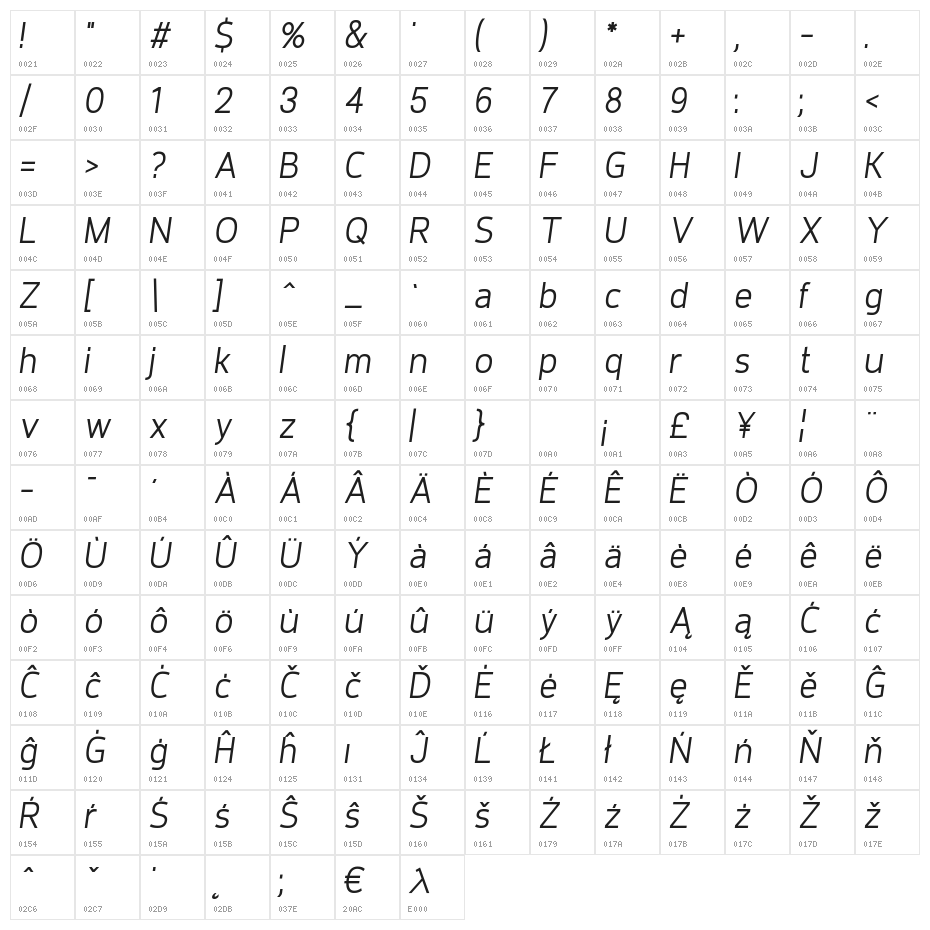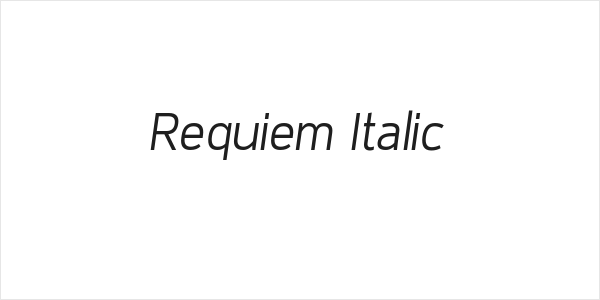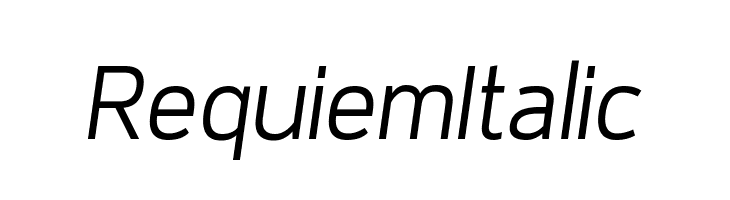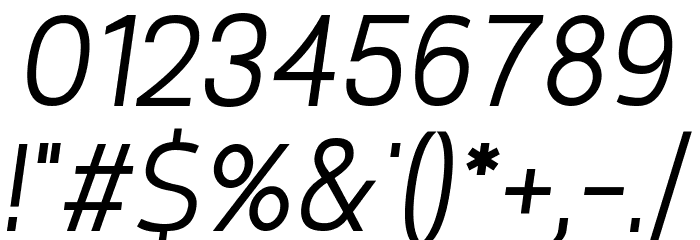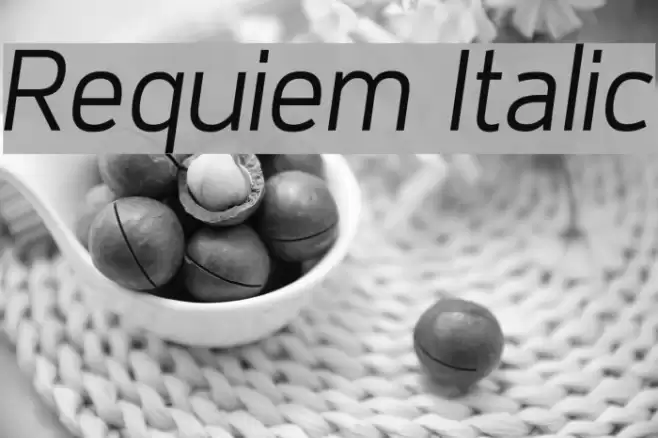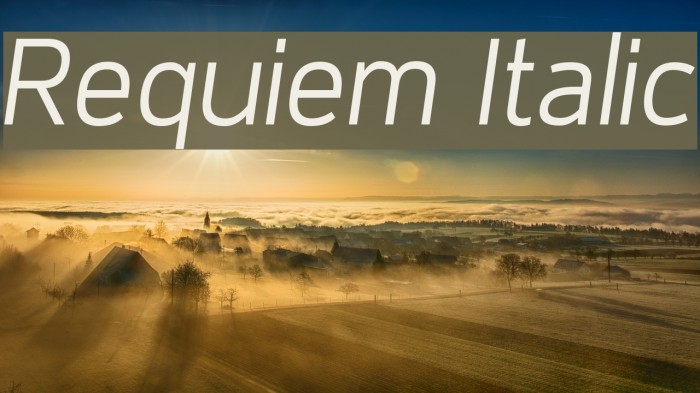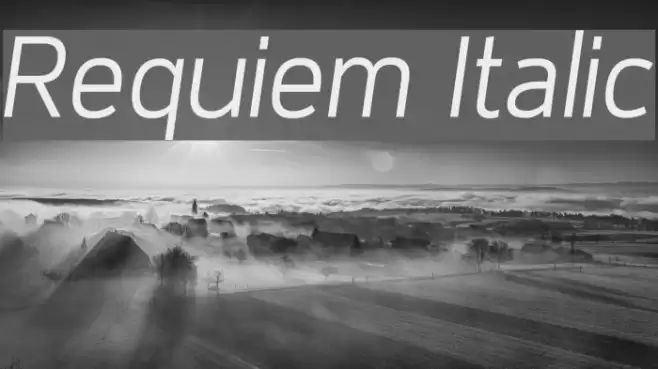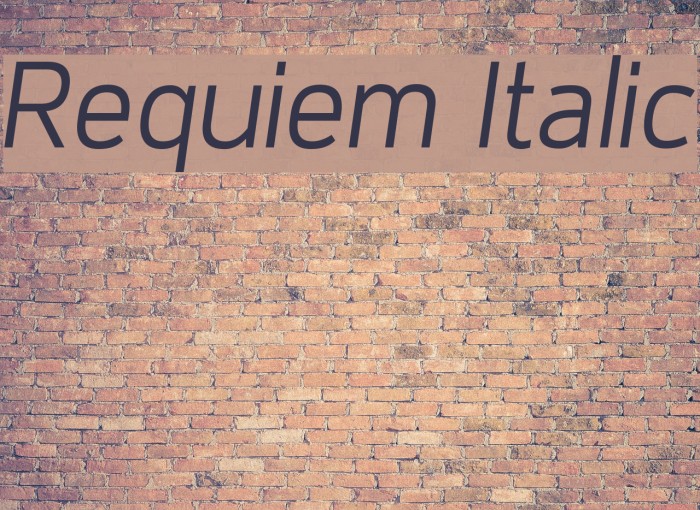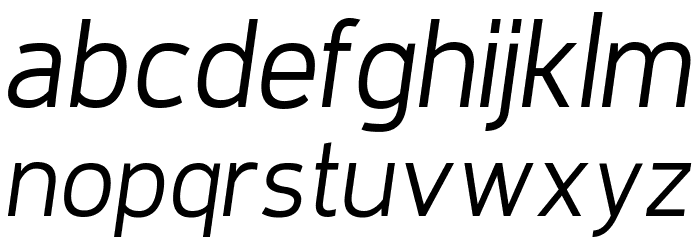
Requiem Italic Font
| Категория | Modern |
| Область применения | Headlines, Body text, Logos |
| Рекомендуемые проекты | Ideal for branding, editorial design, and digital interfaces where a modern and elegant touch is desired. |